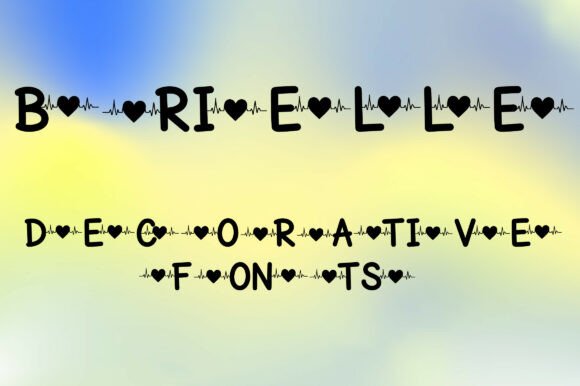
Brielle
Encontrar os elementos de design certos pode ser um desafio, mas Brielle oferece uma coleção excepcional que eleva o seu trabalho instantaneamente.
Trabalhado com precisão, Brielle fornece vetores limpos, tipografia suave e uma licença comercial para sua tranquilidade.
Quer você esteja criando produtos POD (Print on Demand), convites de casamento ou gráficos para mídias sociais, Brielle é a escolha ideal.